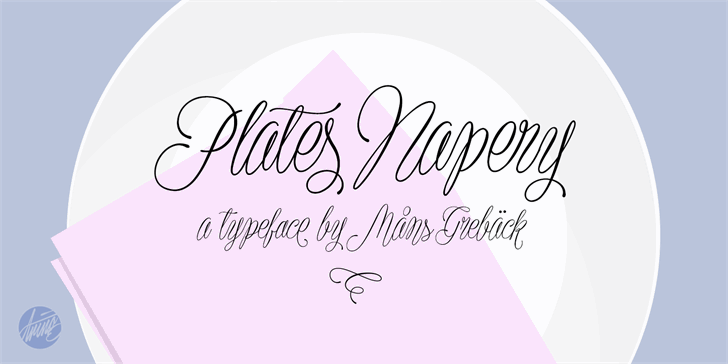
A fonte ‘Plates Napery’ é uma escolha perfeita para estilos modernos e minimalistas, especialmente adequada para criações de design do quotidiano. Suas linhas curvas suaves e detalhes delicados remetem à decoração da mesa, trazendo um toque de elegância aos seus projetos. A designer Hamilton criou uma fonte que transmite tranquilidade e calma com a sua forma suave e fluida. Perfeita para criações de marca ou design gráfico em geral, essa fonte oferece grande liberdade ao seu estilo e pode ser facilmente adaptada para qualquer projeto. Seja para aplicativos como cartões personalizados, revistas internas, elementos web ou simples desenhos digitais, a ‘Plates Napery’ é uma ótima opção para quem busca um equilíbrio entre modernidade e conforto visual. Com seu design minimalista, é fácil adaptar o tipo de texto que deseja apresentar, seja em pequenos detalhes ou em elementos mais visíveis. Em suma, ‘Plates Napery’ é uma fonte atemporal e elegante, perfeita para quem busca uma combinação harmônica entre sofisticação e simplicidade. Visite o site da MansGreback.com/plates-napery para adquirir sua versão comercial dessa fonte única.